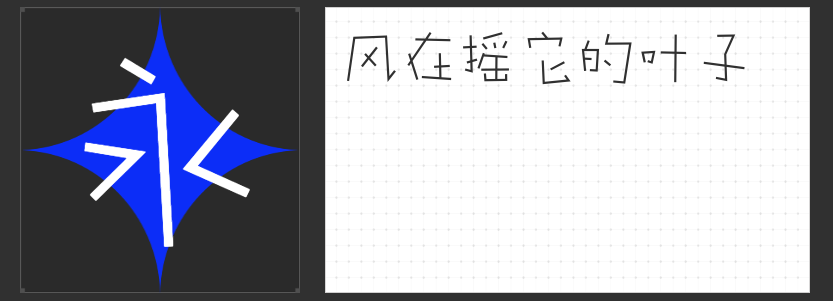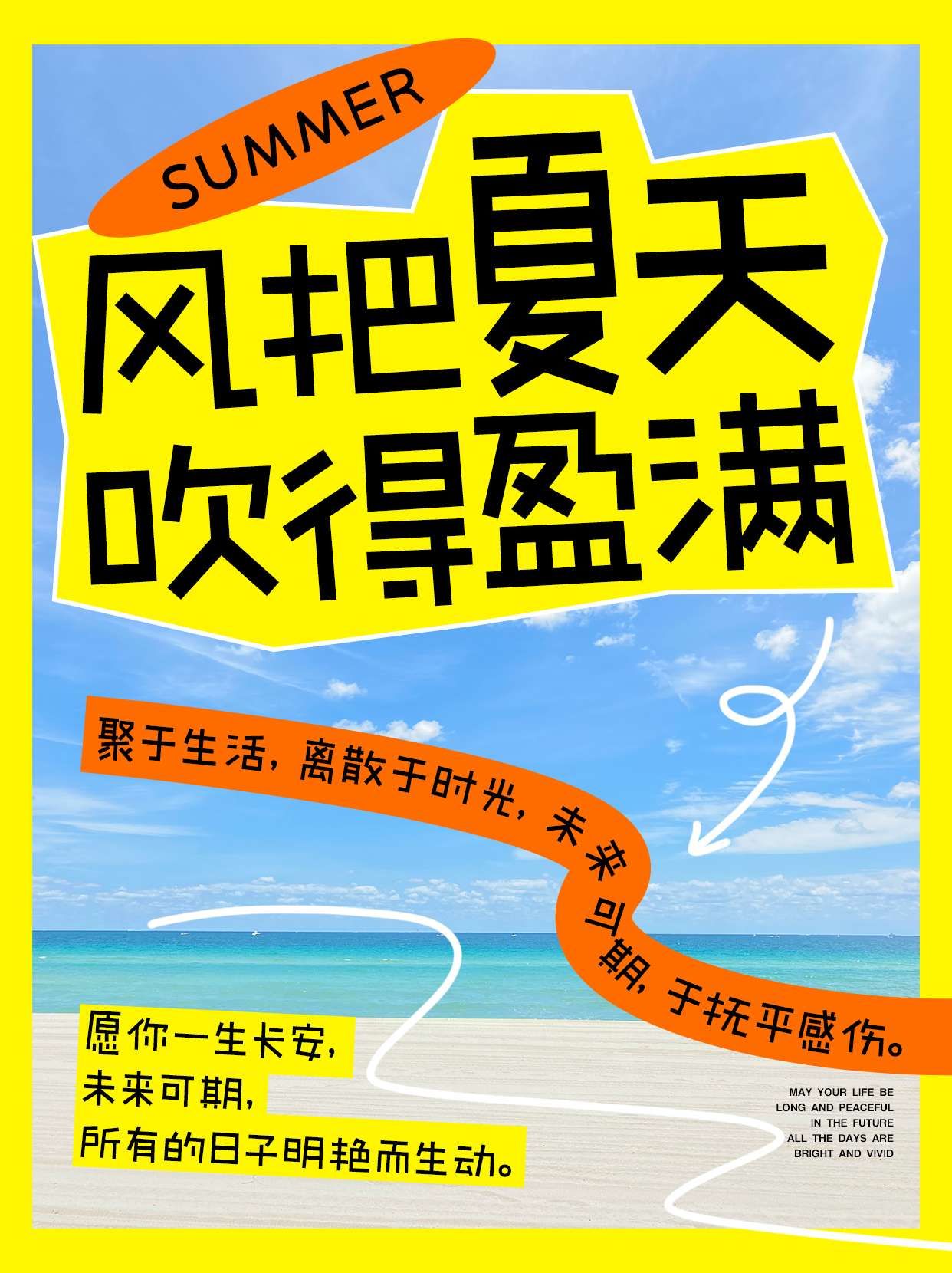
二次元世界的文字魔法:字恋狂系列字体推荐
在二次元的梦幻世界里,文字不仅仅是传达信息的工具,更是展现个性与情感的魔法。今天,就让我们一同踏入字恋狂品牌系列字体的奇妙之旅,探索四款充满魅力的字体。
1.字恋狂澄空 絮风
这款字体如同春日里轻拂的微风,带着手写的温度,字形上松下紧,重心略低,仿佛每个字都在轻盈地跳跃。它的结构灵活多变,字面根据字形自然延展,字间距恰到好处,组合起来如同一首和谐的乐章,既有节奏又不失趣味。笔画粗细均匀,流畅的弧线与利落的直线交织,既保留了手写的随性,又不失设计的精致。
2.字恋狂漫野 鸣风
这是一款直线字体,却藏着不羁的灵魂。结构张弛有度,大小错落,每一字都像是野外自由生长的树木,展现出独特的生命力。笔画简洁而不失力度,去钩处理与“断开”设计,让字体更加通透,灰度均匀,为版面增添了一抹野性的美。
这款字体仿佛被春风轻抚,笔画摇摇晃晃,带着一丝不羁与自由。字体比例夸张失衡,正如被风轻轻吹过的字迹,每一笔都透露着温暖与随性,让人感受到一股来自大自然的温柔力量。
4.字恋狂丸粒简
如果说其他三款字体是风与野的赞歌,那么“丸粒简”就是童真与可爱的化身。圆润的笔画两端,如同糖果般甜蜜,转角处的圆角处理,更是增添了几分亲和力。这款字体,就像是二次元世界里的一颗颗彩色丸子,让人忍不住想要亲近。
字恋狂系列字体,每一款都是对二次元世界的独特诠释,它们不仅仅是文字,更是情感的载体,是梦想的翅膀。在这个充满无限可能的二次元世界里,让我们一起用这些字体,创造出出自己想要的设计吧!